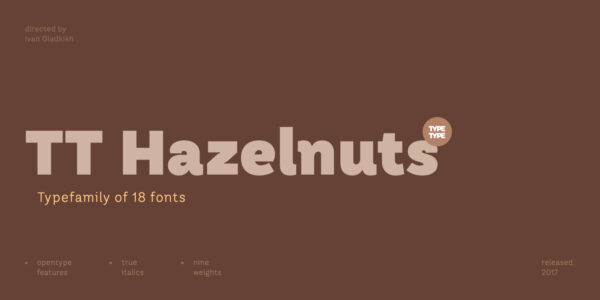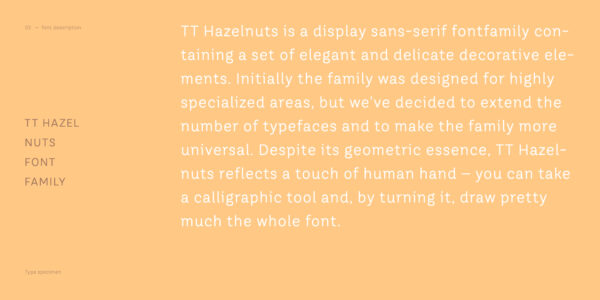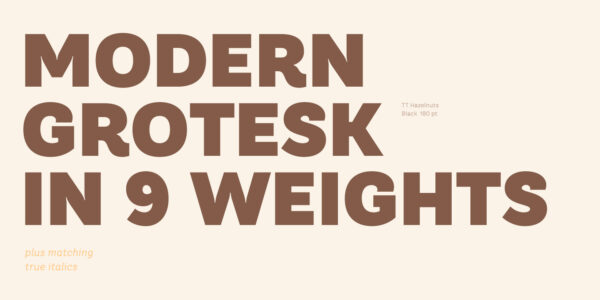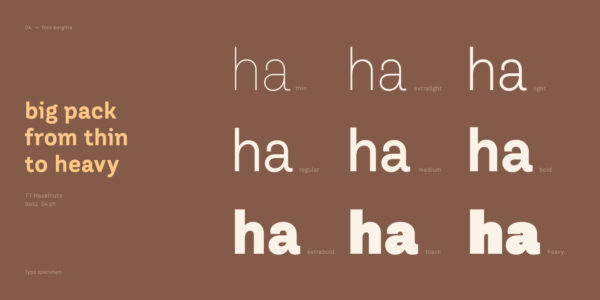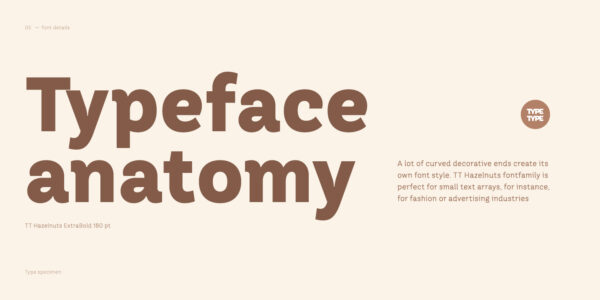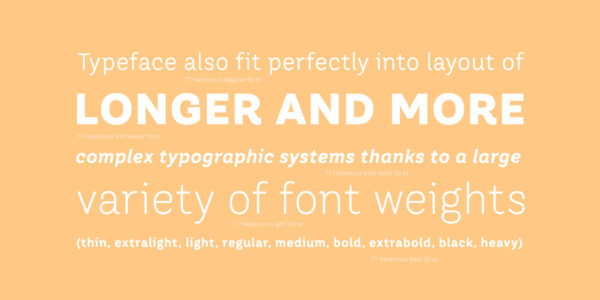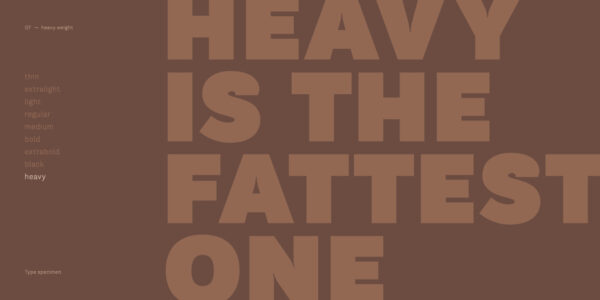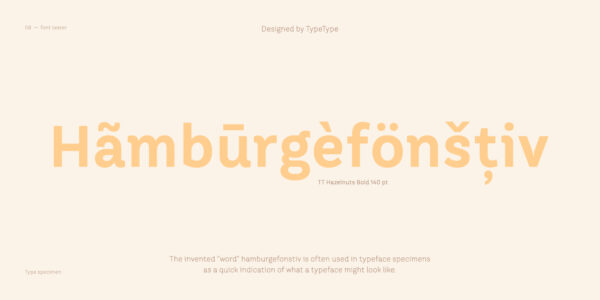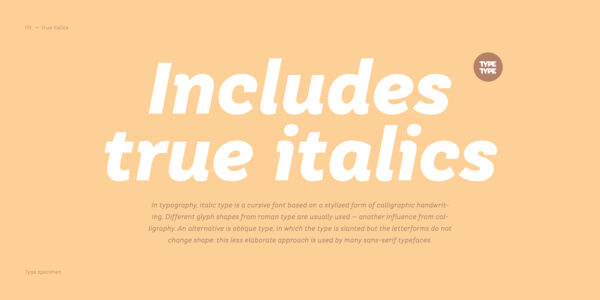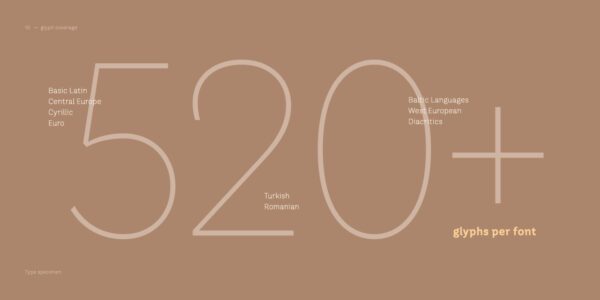
TT Hazelnuts
TT Hazelnuts — ТТ Хейзелнатс
Произносится «ТТ Хейзелнатс». «Hazelnuts» — производное слово от hazelnut, в переводе с английского «фундук». Буквы «TT» являются аббревиатурой названия компании.
TT Hazelnuts — акцидентный шрифт без засечек с плавными и красивыми декоративными элементами.
Акцидентная шрифтовая гарнитура без засечек
Первоначально шрифт задумывался для очень узкой области применения, однако мы решили расширить количество начертаний и сделать шрифт более универсальным. Отлично впишется в верстку более длинных и сложных типографических систем, благодаря большому изобилию начертаний разных весов (Thin, Extra Light, Light, Regular, Medium, Bold, Extra Bold, Black, Heavy), а также присутствию настоящих курсивов.
TT Hazelnuts отлично подойдет для набора небольших блоков текста, например, в модной или рекламной индустрии
О гарнитуре TT Hazelnuts
TT Hazelnuts — это акцидентная шрифтовая гарнитура без засечек с набором плавных и красивых декоративных элементов. Первоначально шрифт задумывался для очень узкой области применения, однако мы решили расширить количество начертаний и сделать шрифт более универсальным. Не смотря на свою геометрическую сущность, в данном шрифте чувствуется след человеческой руки, при желании можно взять перо и поворачивая его нарисовать практически весь шрифт.
Шрифтовое семейство TT Hazelnuts отлично подойдет для набора небольших блоков текста, например, в модной или рекламной индустрии, а также отлично впишется в верстку более длинных и сложных типографических систем, благодаря большому изобилию начертаний разных весов (Thin, Extra Light, Light, Regular, Medium, Bold, Extra Bold, Black, Heavy), а также присутствию настоящих курсивов. Уже становится хорошей традицией включать широкую поддержку OT features в наши новые шрифты. TT Hazelnuts не стал исключением, в шрифте используется большое количество полезных features: ordn, sinf, sups, numr, dnom, tnum, onum, frac, case.
onum | Oldstyle Figures
case | Case Sensitive Forms
frac | Fractions
numr | Numerators